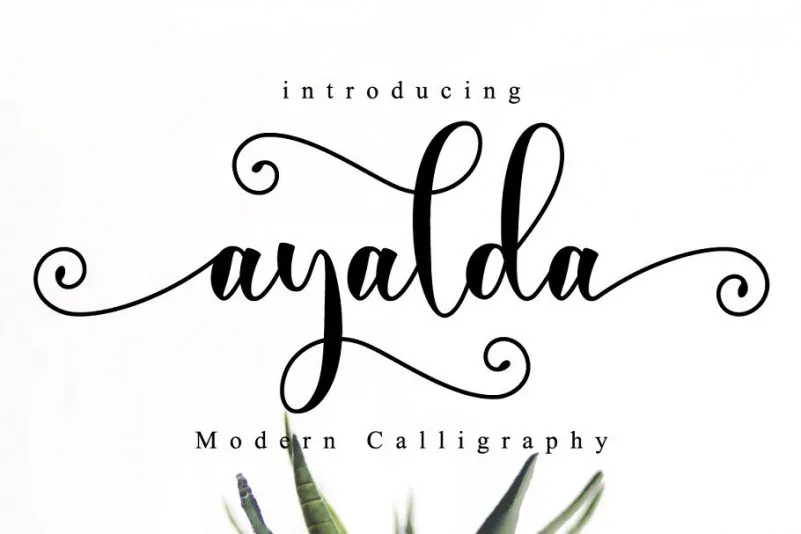
Ayalda Calligraphy Font – Download Grátis
A Ayaldá Font é uma opção perfeita para quem busca estilo elegante no seu projeto. Esta é uma tipografia script com um toque moderno de escrita a mão, inspirado na arte do hálago. Perfeita para criações digitais, ela oferece swashes (dobras) e traços únicos que deixam qualquer design ainda mais singular. A Ayaldá se destaca não apenas por seu formato elegante e delicado, mas também por sua capacidade de transformar pensamentos em realidade através da arte do design. Seja para trabalhos de marca, logomarcas, aniversários ou embalagens de produtos, a Ayaldá é um recurso perfeito. Suas formas suaves e harmoniosas podem ser usadas com facilidade em t-shirts, em designs para pacotes de produto, etiquetas, até mesmo em fotografias e design editorial. A Ayaldá é uma opção essencial para qualquer projeto que busque um tom sofisticado e único. Tornar sua visão única ainda mais poderosa, ela se destaca nos projetos mais diversos sem perder seu encanto e singularidade. A Ayaldá é a fonte perfeita para levar suas ideias de design para o próximo nível.